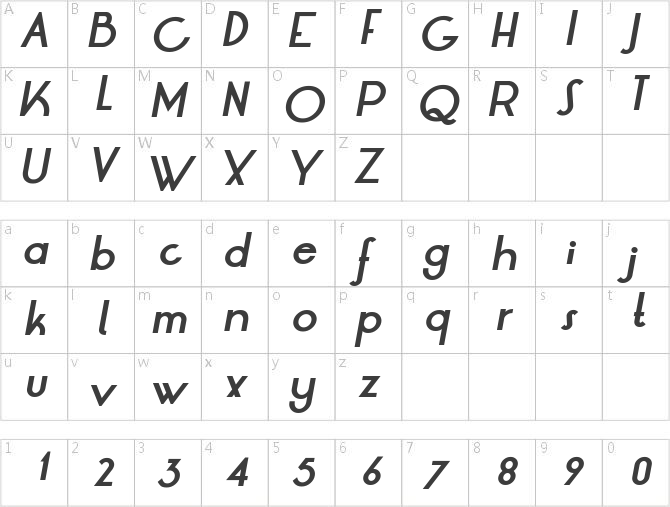
LRT Oksana Bold Italic
LRT Oksana Bold Italic介绍
LRT Oksana Bold Italic字体字库是一款让人赏心悦目、百看不厌的英文字体,适合各类广告和产品包装设计应用,字体大小0.09MB,格式为ttf字体,上传用户是Honor,作者/版权方为未知